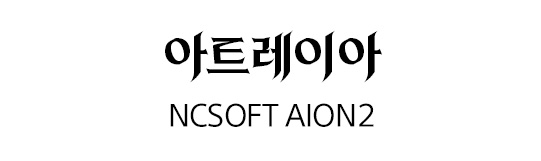
유려한 곡선과 날카로운 세리프
| CLIENT | 엔씨소프트 |
| 프로젝트명 | NCSOFT AION2 전용서체 |
| 스펙 |
1종 Bold (한글 11,172자) 2종 Light, Medium(한글 2,500자 + 영문 94자 + 약물 986) |
| 개발연도 | 2025 |